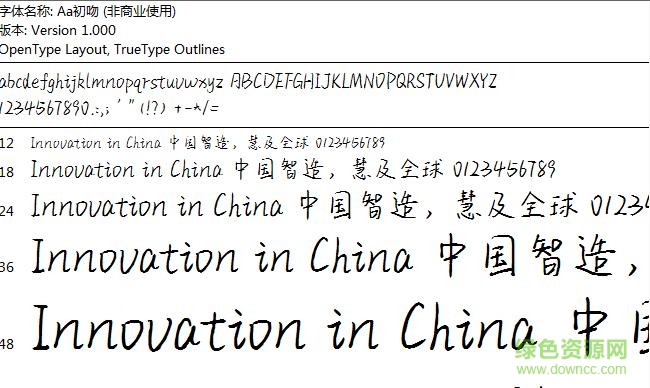
Aa初吻字體ttf
aa初吻字體是aa字體管家中的一款非常好看的中文字體,字體纖細(xì)簡單大方,整體效果十分出色,有喜歡這款字體的朋友歡迎下載使用!
aa初吻字體簡介
aa初吻字體是一款字形娟秀的手寫字體,字體骨骼清秀、遒勁有力,清冽而又優(yōu)雅、從容,令人賞心悅目。特別適合用于需要各種藝術(shù)字體的廣告和文章等!
aa初吻字體